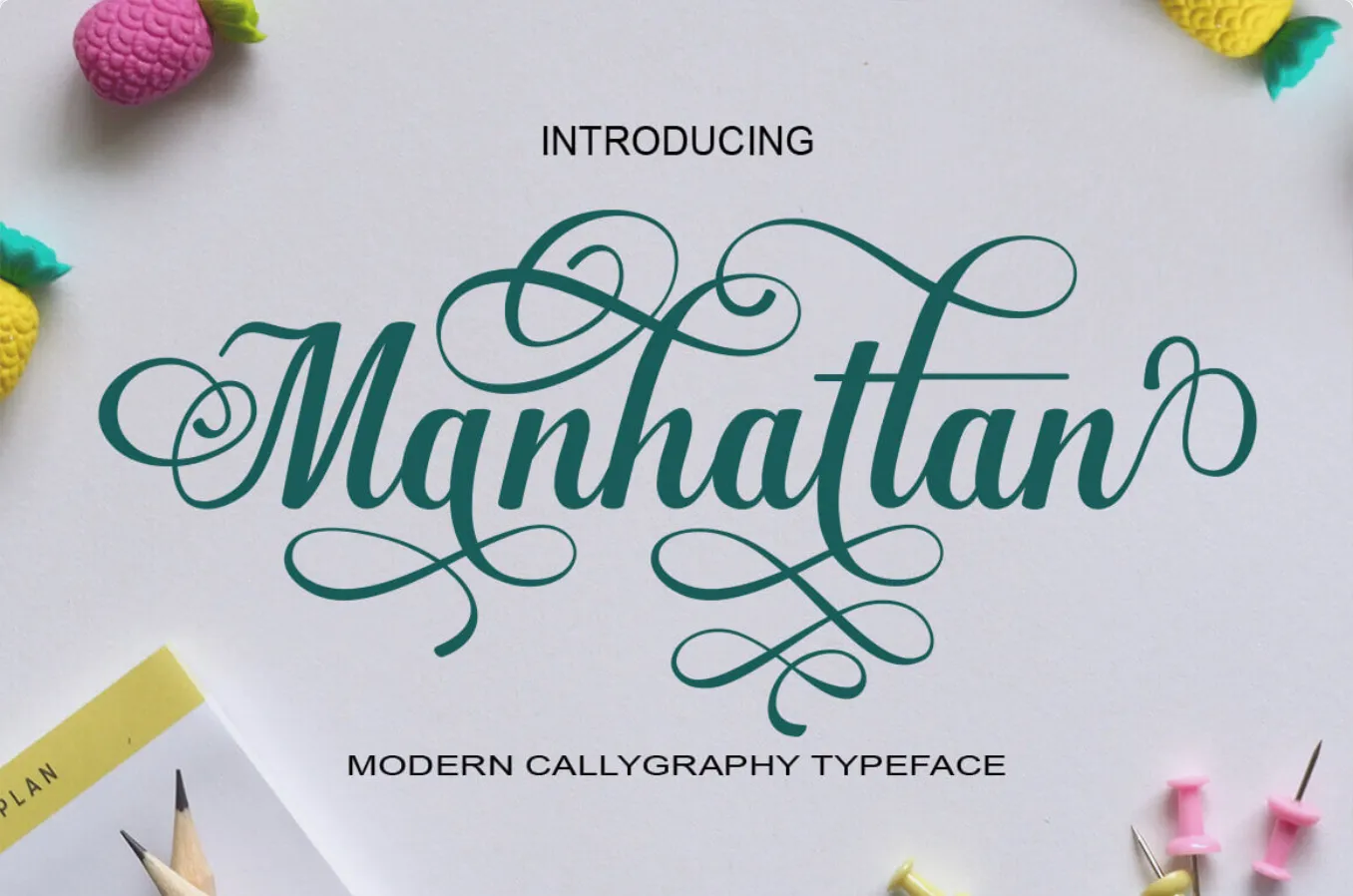
Элегантный современный каллиграфический шрифт Manhattan
Manhattan — это профессиональный современный каллиграфический шрифт, выполненный в элегантном и утонченном стиле. Данный продукт представляет собой цифровой набор символов, предназначенный для использования в графическом дизайне, верстке и оформлении печатной продукции. Шрифт отличается высокой детализацией и эстетичностью, что делает его универсальным инструментом для создания визуально привлекательных проектов.
Продукт обладает широкими техническими возможностями благодаря поддержке функций OpenType, что позволяет пользователю гибко настраивать начертание текста:
- 883 уникальных глифа, обеспечивающих разнообразие форм и стилей.
- Поддержка альтернативных стилей, лигатур и декоративных элементов (swashes).
- Наличие специализированных символов: числители, надстрочные и подстрочные знаки.
- Полная поддержка прописных и строчных букв, а также знаков пунктуации.
- Поддержка международных символов, что позволяет использовать шрифт в текстах на различных языках.